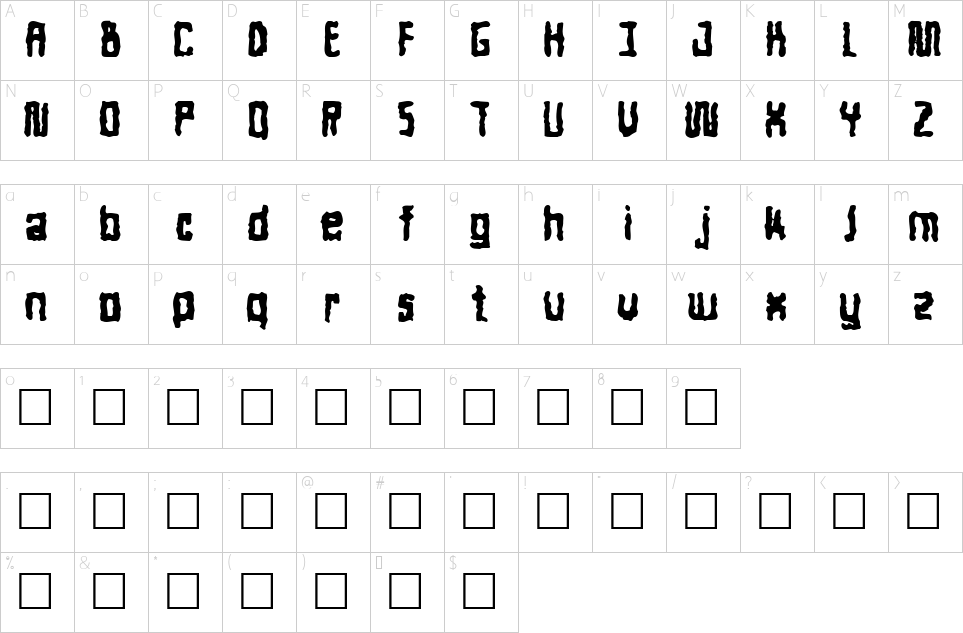
Decline of Western Civilization Font – Download Grátis
Decline of Western Civilization é uma interessante fonte que oferece uma visão distintiva do futuro que se estende à frente dos olhos. Desenvolvida por Kung Fu, esta fonte transmite uma atmosfera sombria e intrigante que remete a momentos de declínio e transformação cultural. A característica da fonte permite que ela seja utilizada tanto no Windows quanto Mac, tornando-a versátil para diferentes necessidades de design. Embora sua influência não possa ser medida em termos de uso pessoal ou comercial, Decline of Western Civilization tem sido baixada mais de 1.653 vezes por artistas e designers interessados nessa atmosfera única. Se você está procurando por uma fonte que brinca com ideias sombrias e transformações sociais, esta fonte é uma opção interessante para explorar.